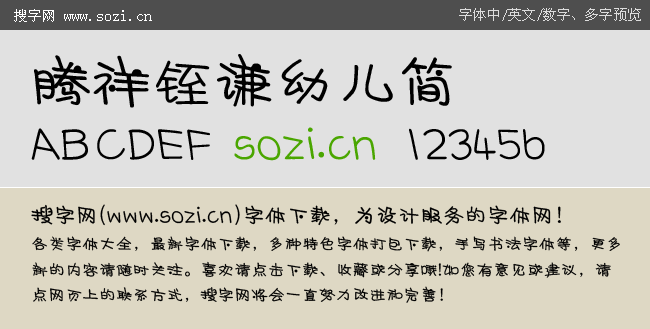
騰祥铚謙幼兒簡(jiǎn)
搜字網(wǎng)給大家提供一款騰祥铚謙幼兒簡(jiǎn)體中文字體下載。此款字為POP手繪字體。由資深硬筆書法家、手繪pop創(chuàng)意設(shè)計(jì)師高铚謙手繪完成原字稿。整幅字風(fēng)格統(tǒng)一、行文規(guī)整,粗看似幼兒寫字歪歪斜斜,仔細(xì)看整個(gè)版面卻個(gè)性鮮明、極具功力。字里行間充滿童真稚趣,彰顯活潑靈動(dòng)的個(gè)性。 本作品可用于出版印刷、廣告設(shè)計(jì)、網(wǎng)頁設(shè)計(jì)、包裝設(shè)計(jì)、屏幕顯示、手機(jī)顯示等。